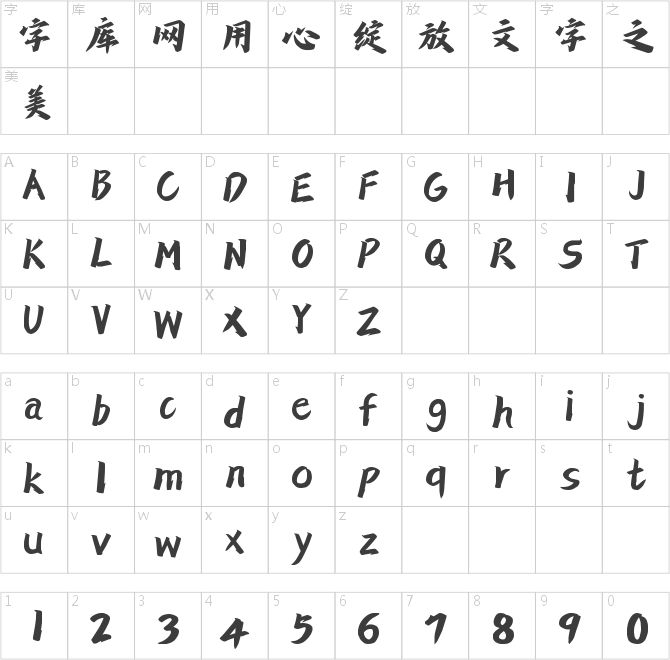
字體名稱(chēng): 字靈拙刻手書(shū)
字靈拙刻手書(shū)
字靈拙刻手書(shū)介紹
字靈拙刻手書(shū)字體字庫(kù)是一款讓人賞心悅目、百看不厭的中文字體,適合各類(lèi)廣告和產(chǎn)品包裝設(shè)計(jì)應(yīng)用,字體大小11.92MB,格式為ttf字體,上傳用戶(hù)是伍佰,作者/版權(quán)方為字靈